¿Ayudan determinadas tipografías a las personas con dislexia?
En el mercado hay varias tipografías, compatibles con cualquier computadora y alternativas a las tradicionales, que aspiran a facilitar la lectura a personas con dislexia. Varios estudios analizan su efectividad
No es raro encontrar, cada vez más, textos adaptados con tipografías especialmente diseñadas para ayudar en la lectura a personas con dislexia. Son las fuentes conocidas en inglés como dyslexia friendly: Dyslexie, EasyReading, OpenDyslexic, Read Regular y Sylexiad, entre otras. Estas fuentes presentan dos características principales:
- Particularidades gráficas del aspecto de las letras para evitar la confusión entre letras con forma similar (por ejemplo, p, b, d y q).
- Mayor separación entre letras y palabras para reducir el efecto de hacinamiento visual: es decir, el perjuicio que causan los elementos visuales circundantes en el reconocimiento de un elemento central.
Sin embargo, no está claro si la evidencia científica apoya la propuesta de los diseñadores de estas fuentes especializadas: que las personas con dislexia leen más fácilmente los textos escritos con ellas. Veamos qué nos dicen los estudios científicos rigurosos al respecto.
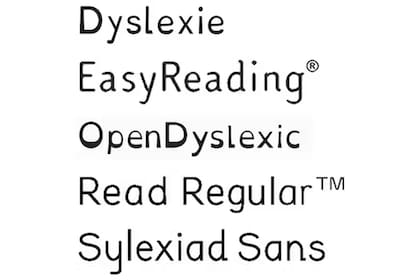
Open Dyslexic
La investigadora española Luz Rello realizó un estudio pionero de los movimientos oculares de adultos disléxicos españoles cuando leían un texto escrito en Open Dyslexic. Los resultados mostraron que la lectura en fuentes Sans Serif (como son Arial, Helvetica o Verdana: fuentes que no tienen “serifa” o remates al final de los extremos) en forma redonda (sin itálica ni negrita) no difiere de la registrada con la fuente especial. Sin embargo, el grupo de personas con dislexia señaló curiosamente que era más desagradable leer en Open Dyslexic que en las otras fuentes.
Un estudio más reciente con escolares norteamericanos con dislexia mostró resultados similares: el uso de OpenDyslexic no mejoró la velocidad ni la precisión lectora. También encontraron que ningún participante prefería esta fuente frente a las habituales Arial y Times New Roman.
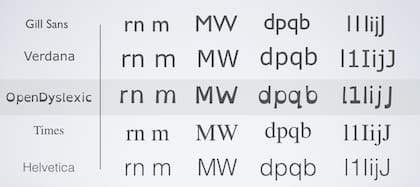
EasyReading
Los efectos de EasyReading han sido comparados con la fuente Times New Roman en un estudio con escolares italianos, con y sin dislexia. La fuente especializada produjo una ventaja en velocidad y precisión lectora en ambos grupos. Esto sugiere que EasyReading simplemente se lee mejor que la Times New Roman.
Desafortunadamente, EasyReading no ha sido contrastada con otras fuentes de la familia Sans Serif, que parecen ser más fáciles de leer, en general, que las de la familia Serif.
Dislexie
Las posibles ventajas de esta fuente han sido analizadas en varios estudios. En un estudio con escolares holandeses con dificultades lectoras no se constató ninguna ventaja de la fuente Dislexie en comparación con las fuentes Arial y Times New Roman.
Otra reciente investigación comparó la ejecución de escolares ingleses con dislexia en distintas tareas de lectura con letras en Dislexie frente a Calibri. Los resultados no mostraron diferencias en la lectura de oraciones ni de palabras aisladas. Dislexie sí mostró cierta ventaja cuando se trataba de decir el nombre de las letras, aunque en realidad esta tarea no puede ser considerada técnicamente como lectura.
En otro estudio con niños australianos con problemas de lectura se encontró que la lectura en Dyslexie era un 7% más rápida que en Arial. Sin embargo, cuando el espaciado entre letras de la fuente Arial se aumentó hasta igualar al de Dislexie, la mejora en la velocidad lectora desapareció. Según los autores del estudio, el efecto de la fuente Dyslexie no se debía al diseño especial de las letras, sino al (mayor) espaciado entre ellas.
No hemos encontrado estudios científicos de calidad sobre las fuentes Read Regular y Sylexiad.
El espaciado entre letras, la clave
Es muy probable que el espaciado entre letras sea el factor clave para facilitar la lectura de personas con dislexia y no la forma especial de las letras.
El beneficio para las personas con dislexia de aumentar un poco el espaciado entre letras de tipologías habituales (manipulación que cualquiera puede realizar con un editor de texto común) se ha visto confirmado por varios estudios en bosnio, español, francés, italiano e inglés.
Aunque también existen algunos estudios con efectos nulos a este respecto, como el realizado recientemente con escolares polacos con y sin dislexia. Al analizar sus movimientos oculares, comprobaron que aumentar el espaciado entre letras no afectó a la precisión, la comprensión, ni a la velocidad de su lectura.
Finalmente, hay que destacar el estudio de Joo y colaboradores, en el que comprobaron que solo un subgrupo de adultos norteamericanos con dislexia leía mejor cuando el texto se representaba con mayor espaciado entre letras, palabras y líneas; mientras que el resto no parecía ser sensible a esas manipulaciones.
Estos autores sugieren la existencia de un subtipo de dislexia con origen en un acusado efecto de hacinamiento visual. Por ello, aumentar el espaciado entre letras, palabras y líneas podría ser de ayuda solo para estas personas, mientras que sería irrelevante para los que padecen dislexia causada por otros factores diferentes.